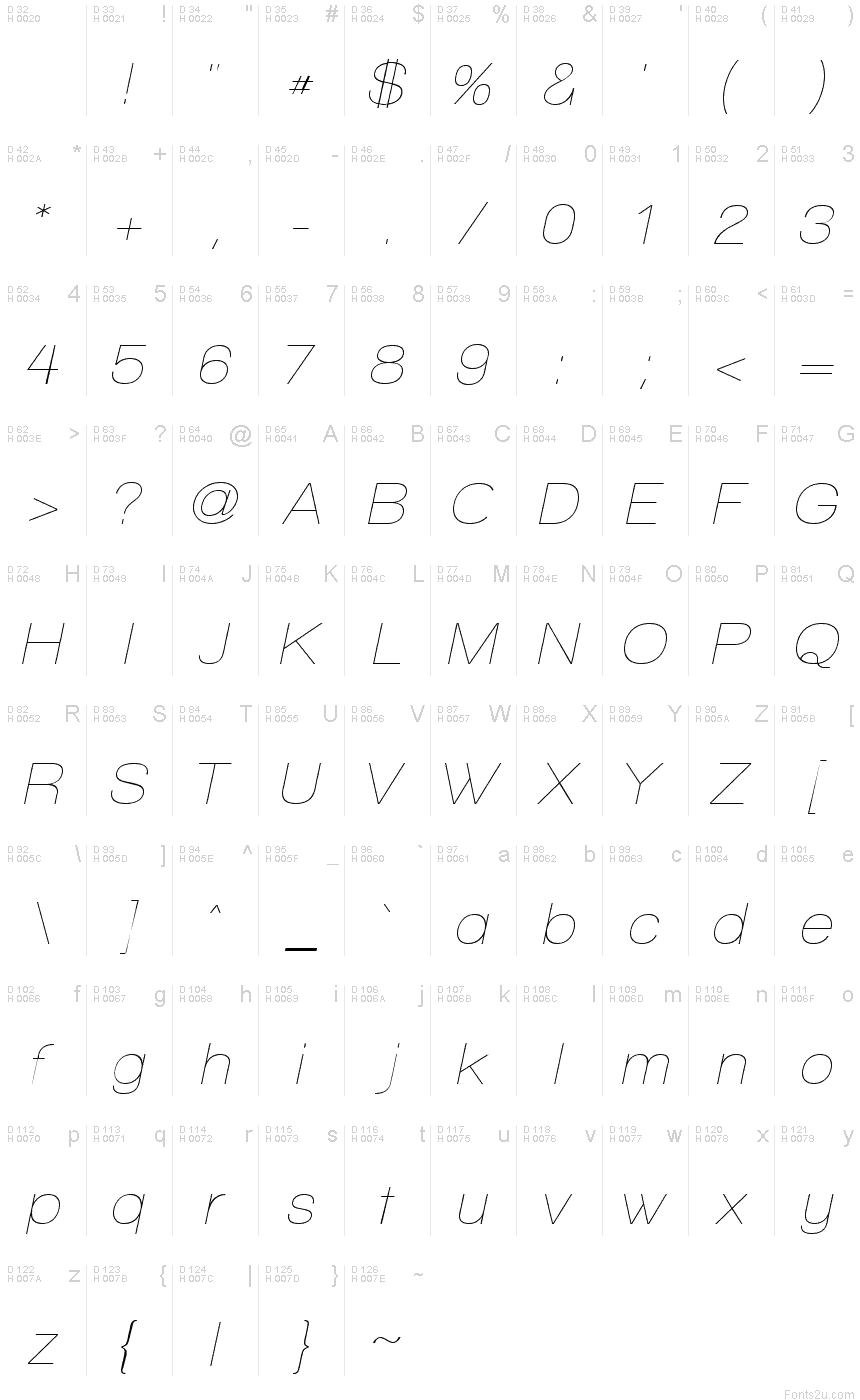
Walkway Oblique
Walkway Oblique di G.M. è un carattere sans serif geometrico gratuito con un mood Art Déco snello e arioso. Le lettere sembrano disegnate a partire da cerchi semplici e lunghi tratti diagonali, conferendo al carattere un ritmo leggero ed elegante, che rimane nitido anziché morbido.
Si adatta perfettamente al branding di moda, ai titoli di locandine, alle copertine di riviste, ai cartelli di apertura e a loghi eleganti dove una leggera inclinazione infonde movimento senza perdere sobrietà. Essendo un carattere gratuito, funziona bene anche per monogrammi e brevi richiami editoriali, poiché le sue forme aperte e le giunzioni sottili come aghi risaltano al meglio quando hanno spazio per respirare.